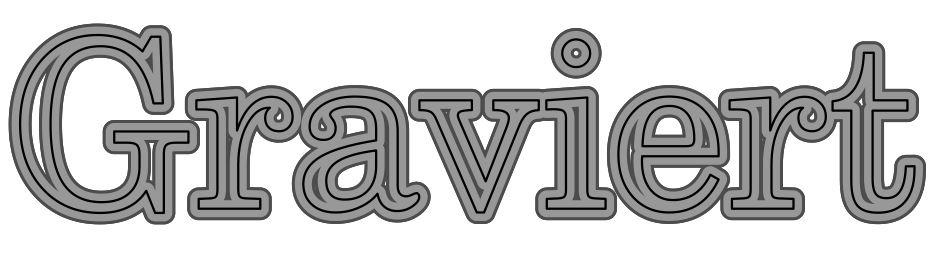
Alternative zu Founders Grotesk für Gravur
Hallo. Ich suche eine Alternative aus dem MS Word Spektrum für Founders Grotesk. Die Schrift ist fürs Branding gekauft und wird dafür auch genutzt. Nur der Graveur, der die Produkte mit einem Badge versieht, kann diese Schrift nicht nutzen, ohne extra einen neuen Satz herstellen zu müssen. Nutzen/Kosten-Rechnung geht da leider nicht auf, darum die Suche nach einem passenden Ersatz. Ich habe auf dem Mac schon geschaut und da denke ich Helvetica, Neue Helvetica geht so in die Richtung. Hab aber das Gefühl, es ist noch zu satt/voll. Es ist nur annähernd gleich. Hätte hier jemand einen Vorschlag?
Ein passender Ersatz müsste aber doch vom Graveur kommen, denn das Kosten-Nutzen-Problem hast du ja bei allen Schriftarten, die vom Graveur erst mal als "neuer Satz" hergestellt werden müssen. Meint er damit die Umsetzung des Fonts in eine gravierbare Linie?
Ich würde zunächst mal seine Vorschläge einholen. Dann kannst du immer noch entscheiden, ob a) was Passendes dabei ist oder b) die Kosten doch nicht so hoch sind, weil es halt innerhalb des Brandings bleiben soll oder c) ein anderer Graveur angefragt wird, der z.B. ätzt, was wiederum mit der Founders als Vorlage gehen sollte.
Danke dir. Der Graveur arbeitet mit allen Schriften, die sich in WORD vorinstalliert finden. 😕 Mir wurde gesagt, ich solle eine Schrift vorschlagen. Ich bin fast dafür die Helvetica/Neue Helvetica zu nehmen. Direkten Kontakt mit dem Graveur hab ich nicht. Sonst hätte ich das bereits so vorgeschlagen, wie du es geschrieben hast, er soll einen Ersatz vorschlagen, der passt.
Aber dann muss er den »Satz« doch so oder so anfertigen. Oder will er in Rechnung stellen, dass er mit der Founders Grotesk zusätzlich eine Schrift installieren muss? :-?
Ich habe auf dem Mac schon geschaut und da denke ich Helvetica, Neue Helvetica geht so in die Richtung. Hab aber das Gefühl, es ist noch zu satt/voll. Es ist nur annähernd gleich. Hätte hier jemand einen Vorschlag?
Als kostenfreie Alternative würde ich mir mal die Work Sans ansehen:
Aus der Microsoft-Word-Sammlung fiele mir momentan nur noch die Franklin Gothic ein.
Irgendwie finde ich es etwas, nun ja, merkwürdig, wenn ein Graveur Outline-Schriften verwendet.
Es ist natürlich richtig, dass man so eine weitaus größere Auswahl an Schriften hat, als den doch recht beschränkten Satz an Singleline-Gravierschriften, welche mit der Graviersoftware geliefert werden, aber Outline-Fonts haben hier einen gewichtigen Nachteil:
Dadurch, das der Fräser dann nicht die Innenfläche der Buchstaben-Outlines füllt, wie beim Druck, sondern eben die Außen-Kontur der der Buchstaben abfährt wird die Schrift immer etwa um die Frästiefe verfettet.
Hier habe ich das mal versucht zu illustrieren. Die grauen Flächen sind die gefrästen, 45° Flächen, die dunklen Linien sind die Kanten der Gravur. Deutlich ist so die Verfettung der gravierten Outline-Schrift sichtbar.
Laser oder Ätzgravur geht natürlich mit Outline-Fonts, das Ergebnis ist aber dann deutlich eher "technisch" und nie richtig sauber.
Ganz so ist es ja nicht – der Graveur verwendet die Outline-Schrift nicht zur Gravur, sondern um davon eine fräsbare Version für seine Maschine zu erstellen. Das, was der TE als "Satz erstellen" bezeichnet hat. Dann kommt eben nicht das von dir skizzierte Ergebnis heraus, sondern eine Gravur, die optisch dem gedruckten Ergebnis des Outline-Fonts entspricht.
Damit der Kunde schon mal in Word selbst "gestalten"  und der Graveur dies dann ohne großen Aufwand und kostengünstig herstellen kann, geht er eben von Schriften aus, die fast jeder zur Verfügung hat.
Ich denke auch, dass ›Schriften aus Word‹ hier als Synonym für Systemschriften zu verstehen ist. Das hört man so ja allzu oft. Ob da dann Helvetica dazugehört :-?Müsste man mal nachfragen. Ansonsten eben Arial, oder wirklich einen Anbieter suchen, der das mit Laser macht und die richtige Schrift verwenden kann.
So richtig verstehe ich aber auch nicht worum es eigentlich geht. Ist das eine einmalige Sache? Soll da eine ganze Reihe von Produkten gelabelt werden? Soll dort eine Marke aufgebaut oder geführt werden? Dann würde ich dringendst davon abraten, die durch ›Word-Schriften‹ zu verwässern …
Könnte man dem Graveur dann nicht einfach eine PDF mit der Gestaltung in Founders Grotesk als Zeichenwege schicken?
Für mich klingt das gerade alles nach der Art Graveur, die ich meiden würde. :shock::-?
Kann man – der Graveur müsste dann aber trotzdem die Vorlage in Maschinensprache für seine Graviermaschine umsetzen (aka "Satz erstellen"), was mit Kosten verbunden ist, was der TE ja vermeiden möchte.